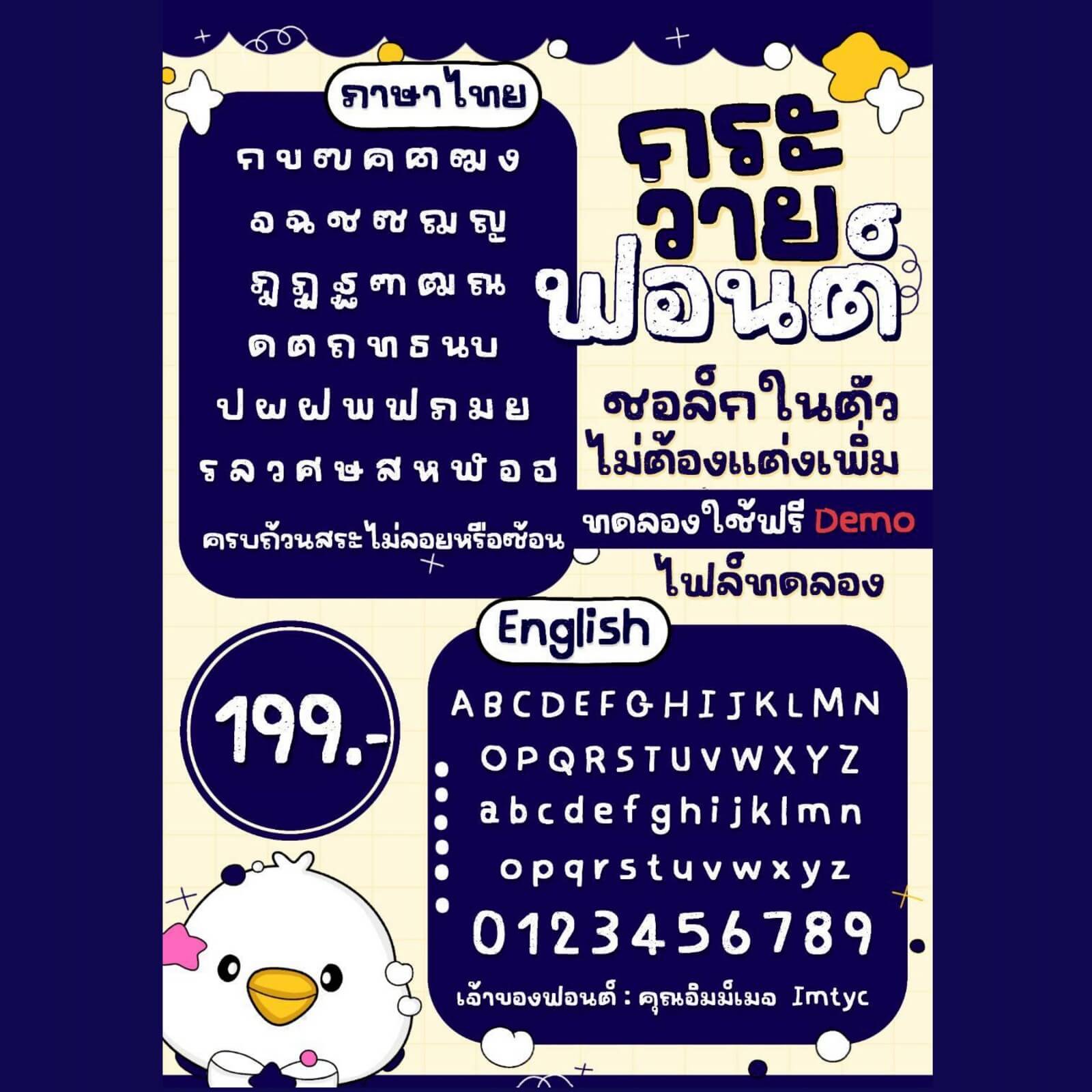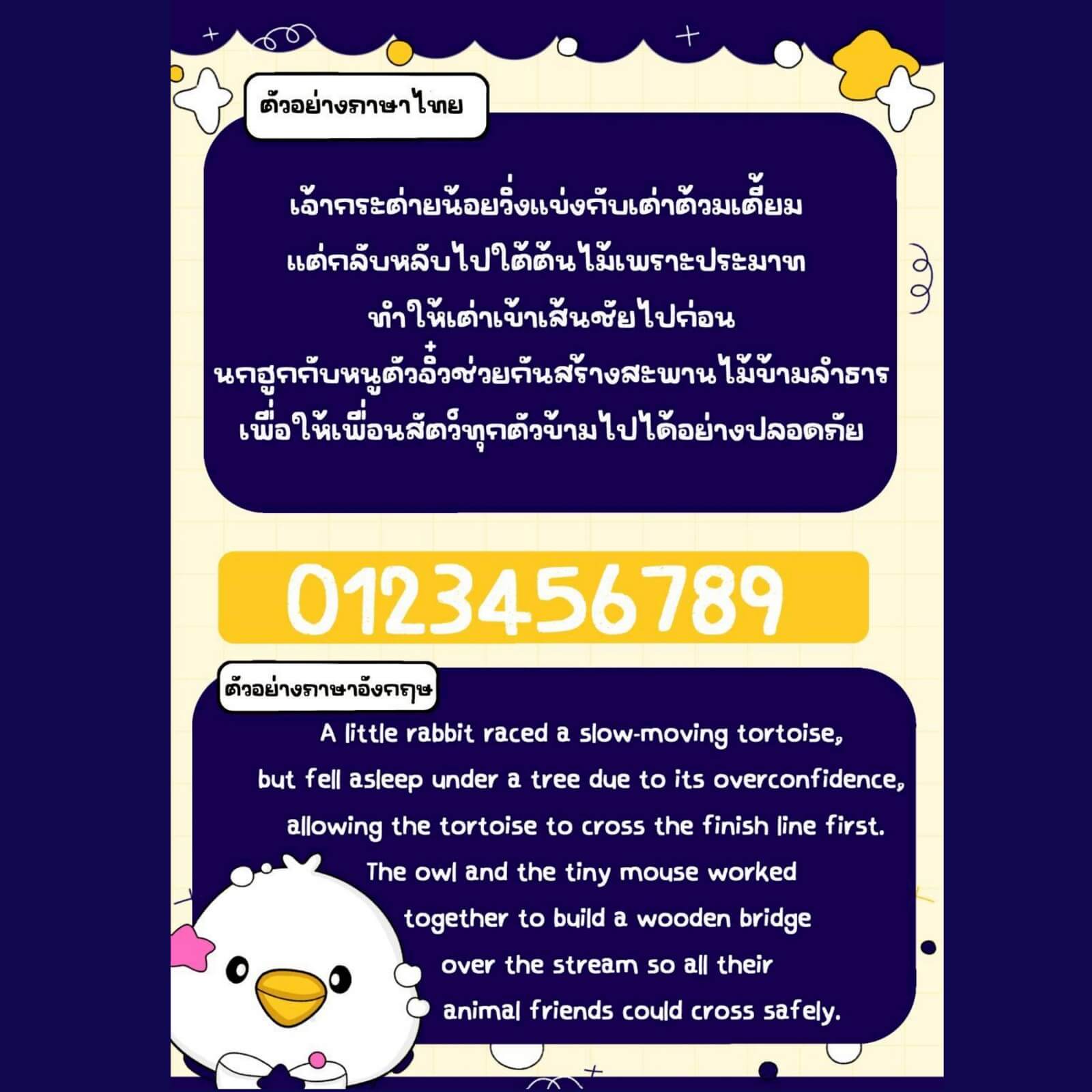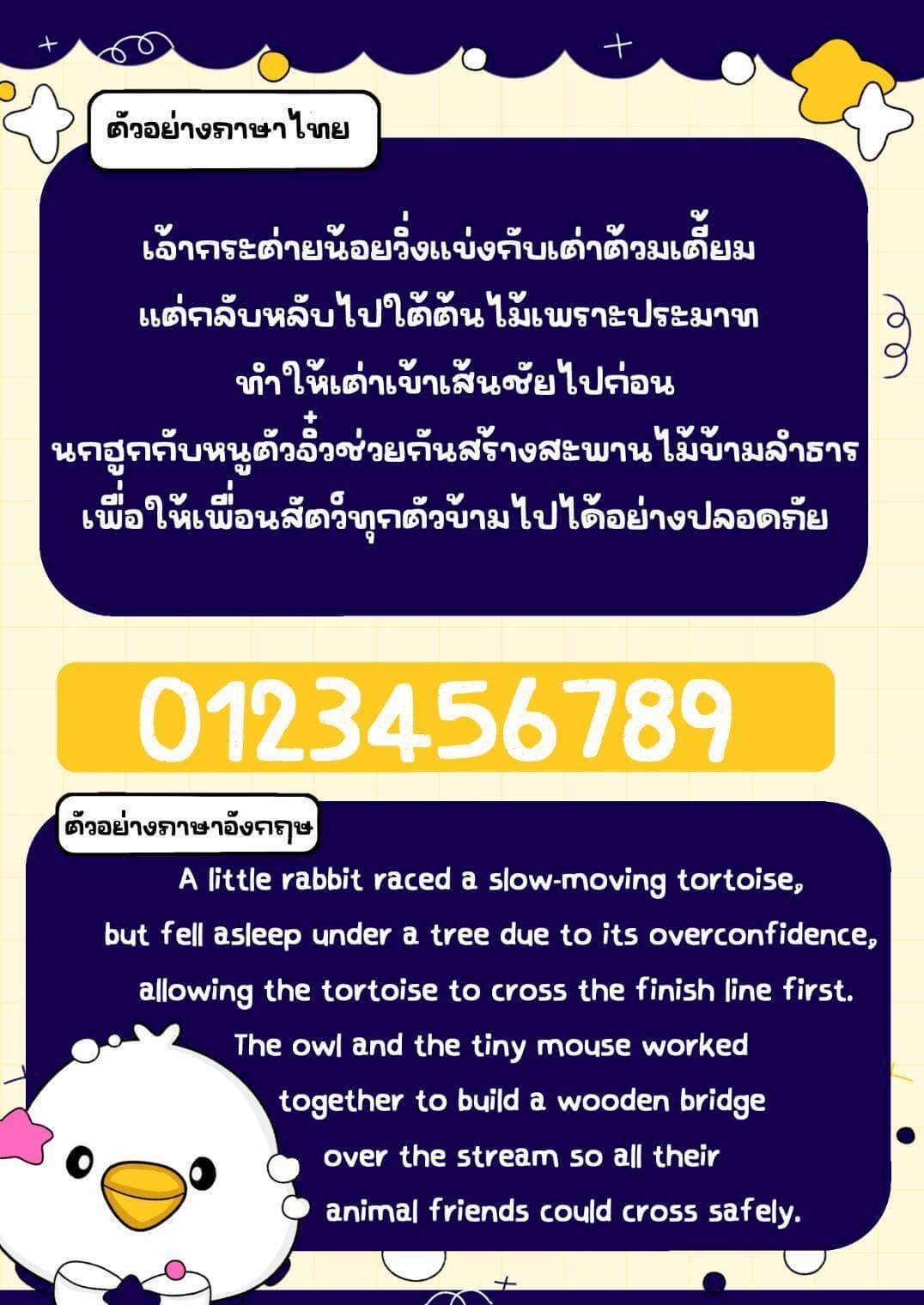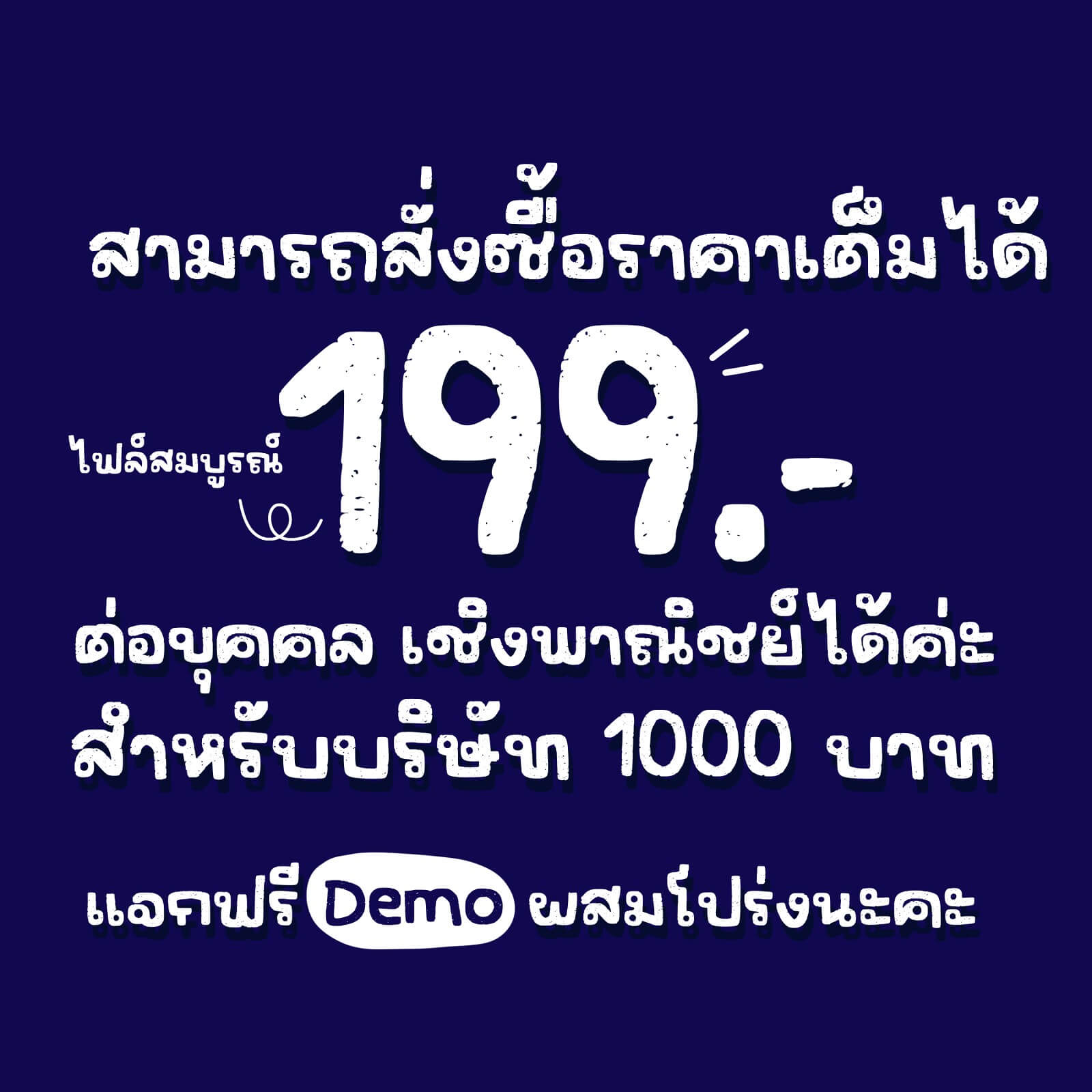
แจกฟรี!! กระวาย ฟอนต์ – ฟอนต์เส้นหนา เท็กซ์เจอร์เหมือนเขียนด้วยชอล์ก ฉลุ ไม่ต้องแต่งเพิ่ม อ่านง่าย ใช้แล้วน่ารักกับทุกงานเยยย
เหมาะกับทุกสายครีเอเตอร์ ไม่ว่าจะใช้ทำป้าย ข้อความ โพสต์ หรือคอนเทนต์น่ารักๆ
กระวาย (IMTYC Kra-wai)